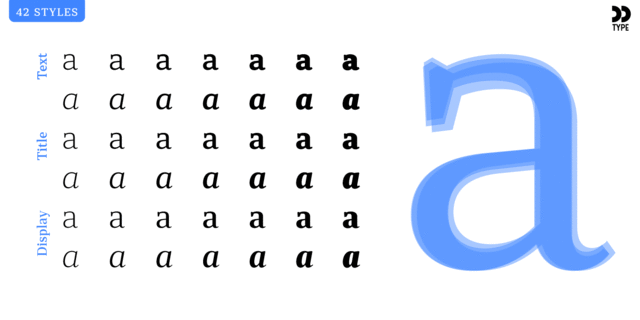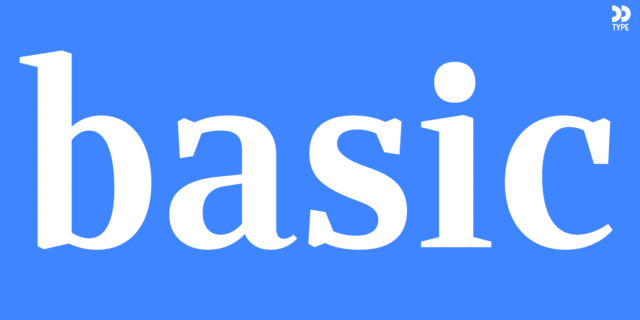
Rolleston Display – часть шрифтового семейства Rolleston. Его 14 начертаний специально адаптированы для акциденции, например крупных надписей на плакатах и обложках.
Rolleston – строгое шрифтовое семейство с клиновидными засечками. Гарнитура содержит 42 начертания, по 14 для трех оптических размеров: Text, Title, и Display.
Гарнитура поддерживает десятки языков на латинице и кириллице, содержит различные опентайп-фичи, можество лигатур и большой набор альтернативных глифов. Это позволяет создавать уникальные заголовки и красивые сбалансированные тексты.
Шрифт разработал Олег Лищук в 2018 году.
Ассоциации c начертанием Rolleston Display MediumКачества и характер:
убедительный, серьезный, ровный, гармоничный, техничный, современный, точный, логичный, статичный, культурный, образованный, устойчивый, умный, стабильный, твердый, солидный, эффектный, модный, качественный, элитный, дорогой, богатый, городской, острый, классический, интеллигентный, аристократичный, салонный, торжественный, звонкий, благородный, мастерский, художественный, изысканный, музыкальный, красивый, прекрасный, блестящий, роскошный, эстетичный, знаменитый, драгоценный, отборный, комильфо, оригинальный, глянцевый, ювелирный, утонченный, гордый, серебрянный, серебристый, театральный, драматичный, творческий, сексуальный, выразительный, яркий, гламурный